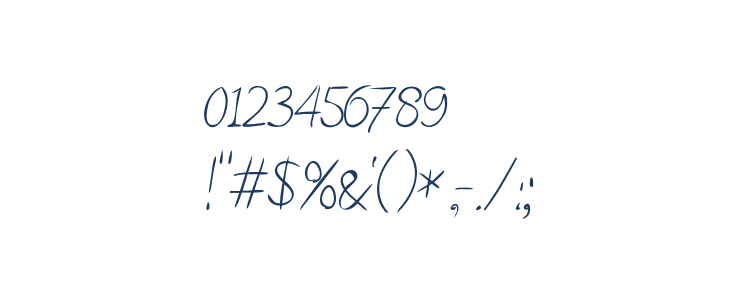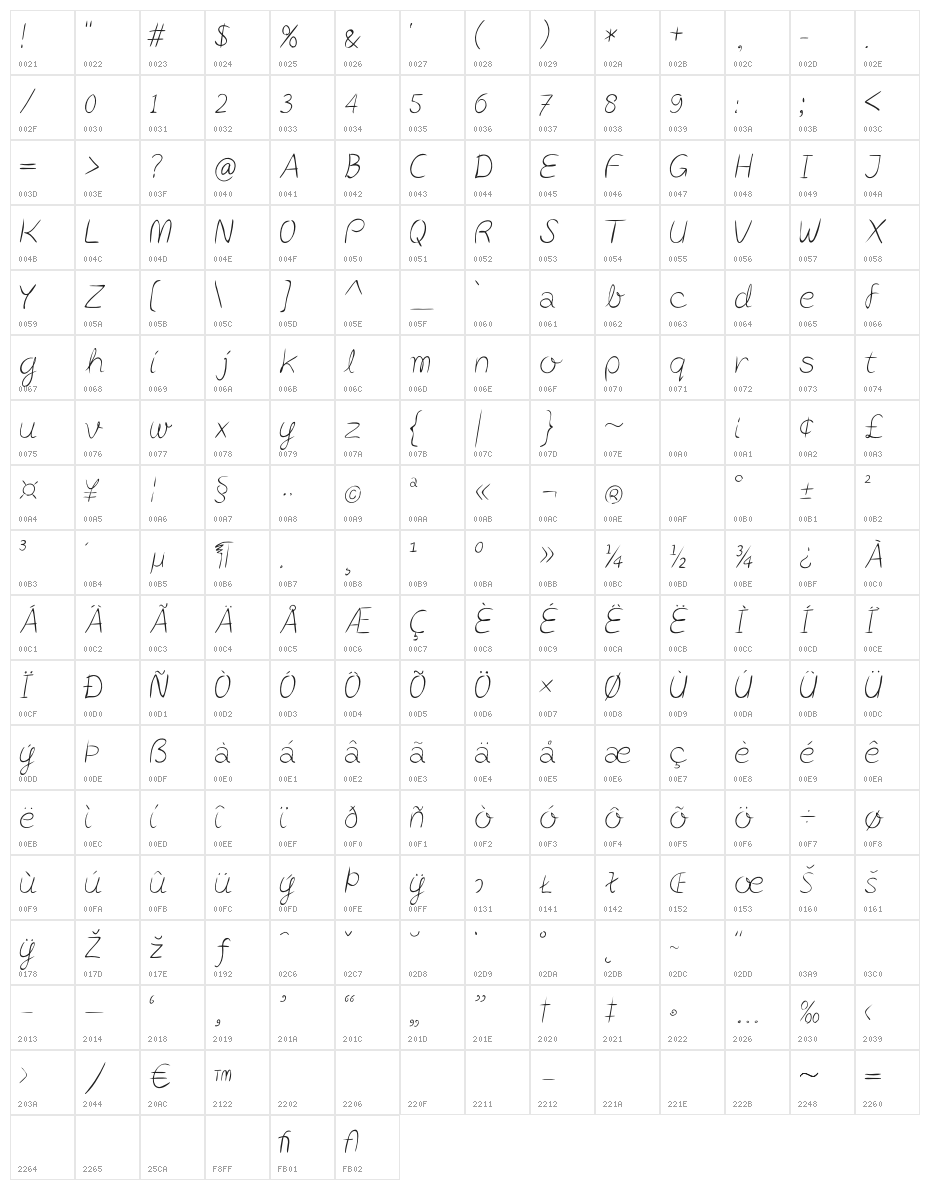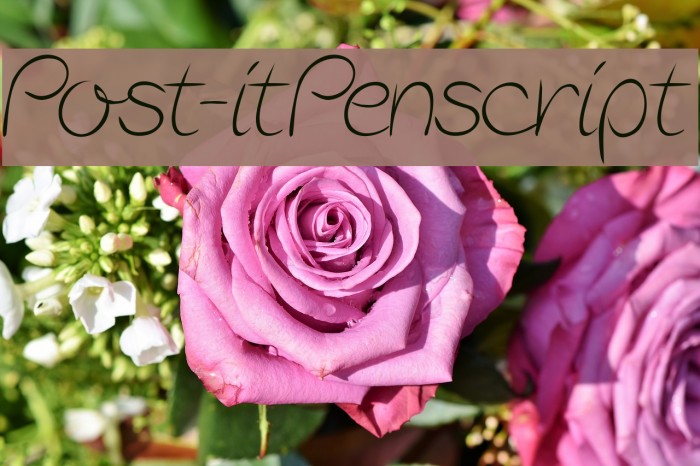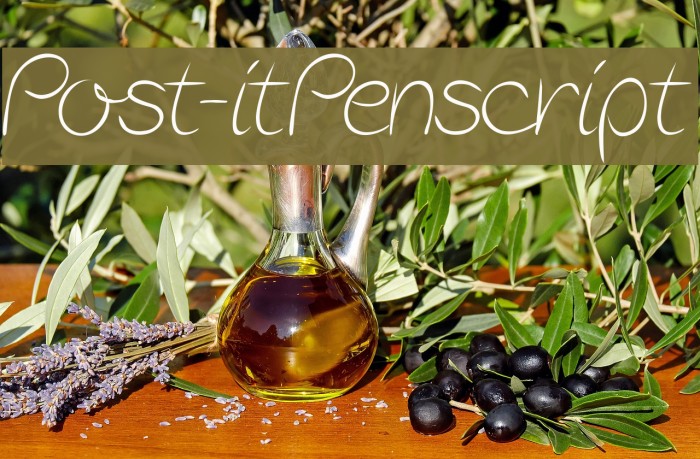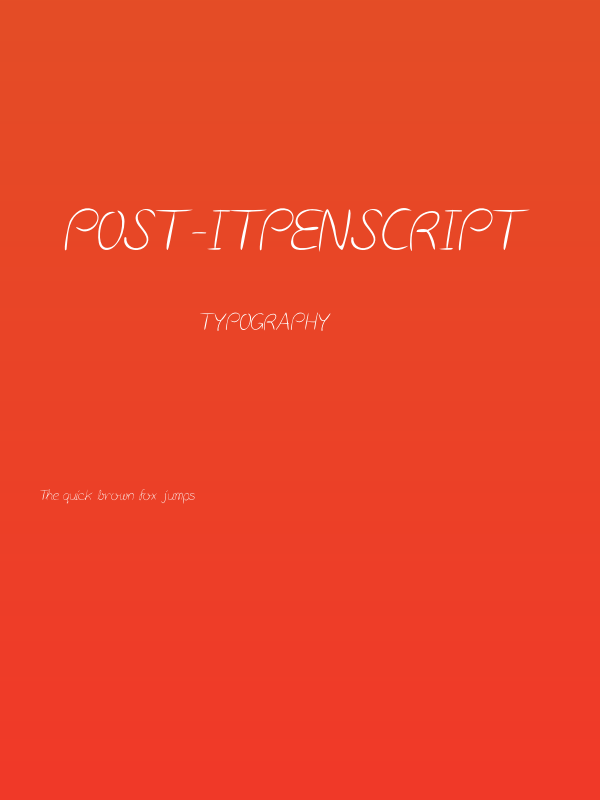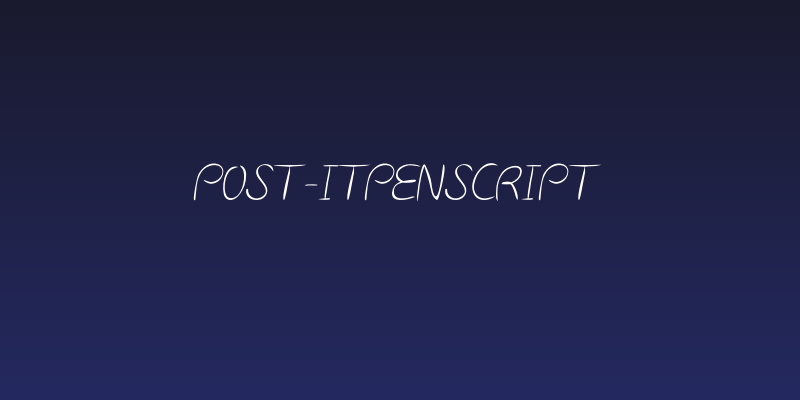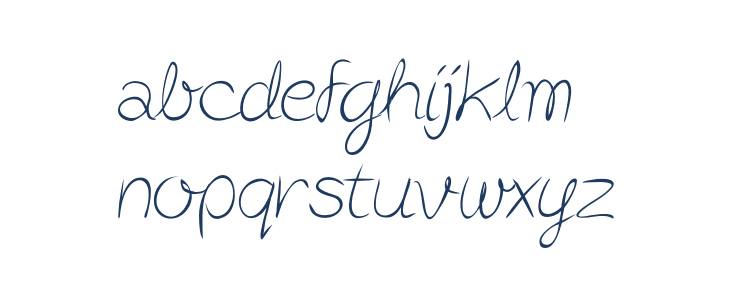
Post-itPenscript Font
| Stile generale | Elegant, Handwritten |
| Caso d'uso | Logos, Invitations, Personal Branding |
| Progetti proposti | Ideal for wedding invitations, greeting cards, personal branding, and artistic projects that require a personal, elegant touch. |